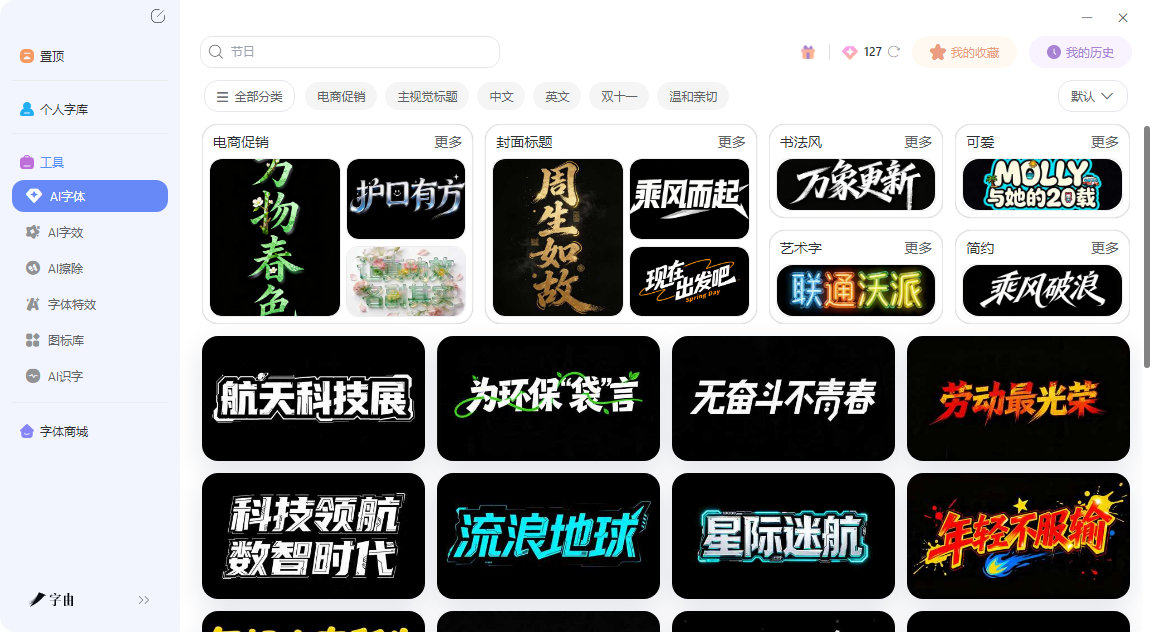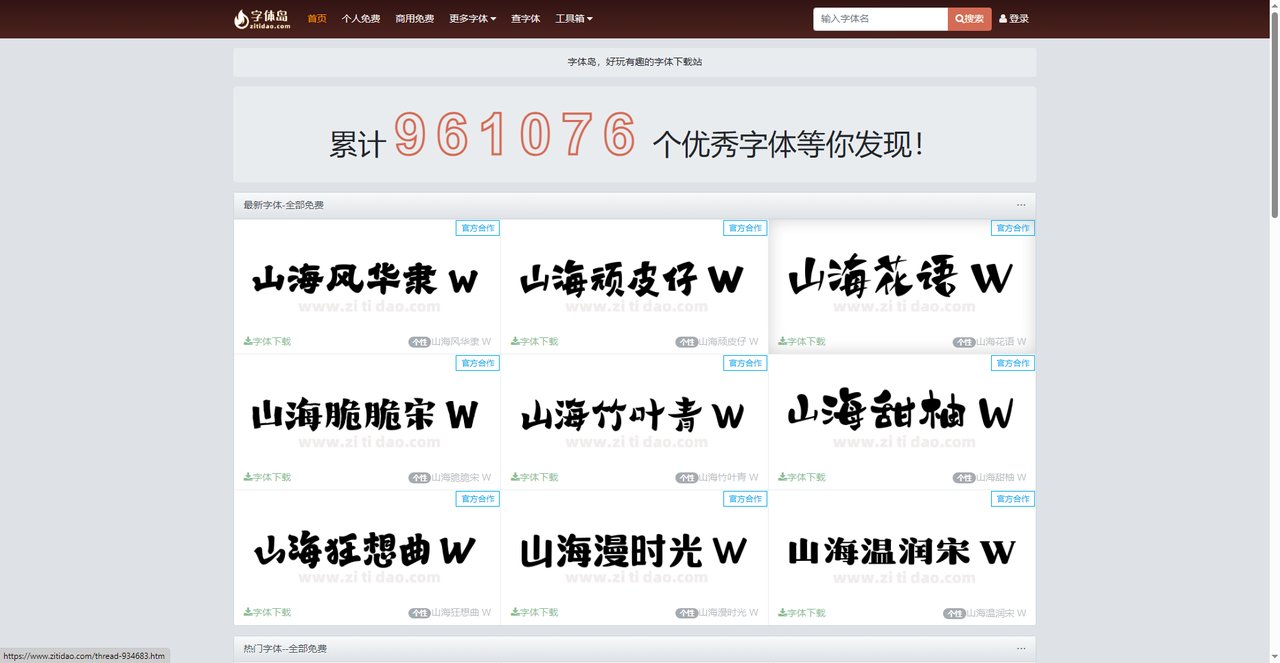
中文字体下载不用愁:看这篇中文字体下载网站精选
中文字体下载这件事,看起来简单,做起来全是坑。搜到一个字体站,点进去广告比内容多;好不容易找到下载按钮,下来一个压缩包,解压后还得自己判断放哪个文件夹;装完了打开PS发现字体没出现,又要重启软件。更麻烦的是,你永远不知道这款字体能不能商用——页面写着“免费”,但那个“免费”到底是免费下载还是免费商用?没人告诉你。这篇文章先介绍一个不用下载安装的方案——字由,然后补充4个传统下载站。看完你就知道,中文字体下载可以不用那么折腾。
打开字由客户端,上万款字体——包括中文字体——都在里面。字由收录了超过20000款字体资源,免费商用中文字体超过1000款,涵盖思源黑体、思源宋体、优设标题黑、阿里妈妈东方大楷等热门款。你只需要找到喜欢的字体,点一下“激活”,字体立刻出现在PS、AI、Word的字体列表里。不用解压,不用复制到C盘,不用重启软件。换电脑登录字由账号,之前激活的字体一键同步,不用重新下载。版权方面,字由专门做了“免费商用”筛选标签,点一下,所有能在商业项目里放心使用的中文字体一次性列出来。每款字体的详情页都有版权方的授权文件链接。
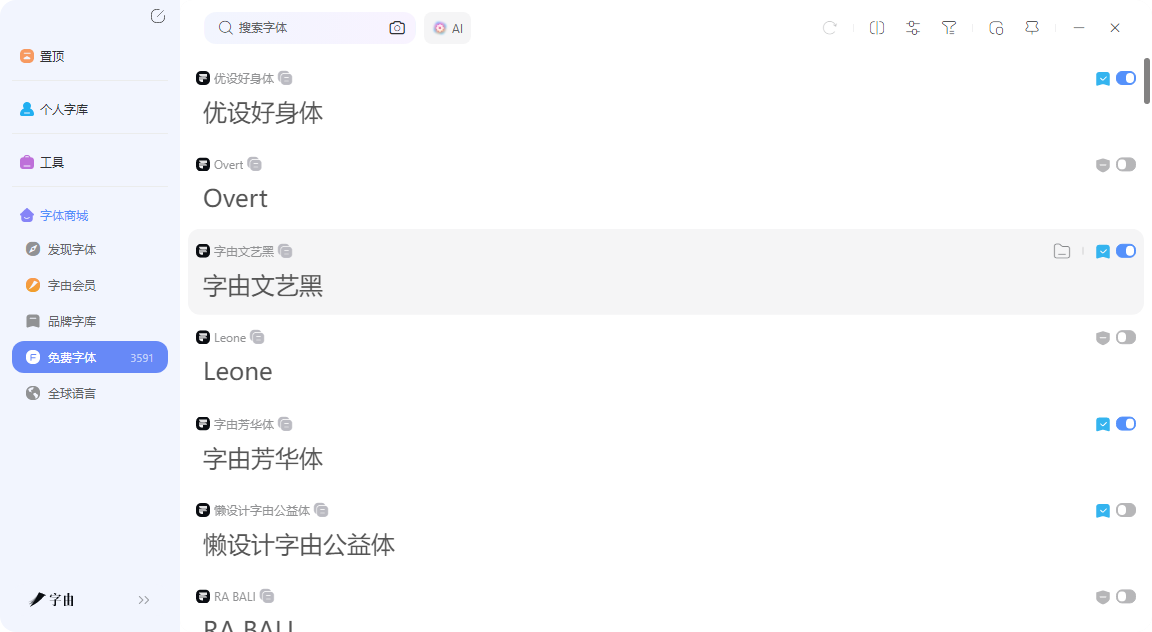
字由还有AI字体功能:输入文案,选个国潮风或书法模板,10秒生成一张艺术字图片,下载PNG就能用。这对那些不想折腾安装、只想快速出效果的用户来说,比传统下载站方便太多。
传统下载站不是不能用,但它们的模式停留在20年前。字由把“中文字体下载”这件事,从“搬运文件”变成了“云端激活”。你不需要关心字体文件存在哪、怎么传、怎么装。你只需要在字由里点一下“收藏”和“激活”,剩下的全部交给云端就可以了。
2、字体岛
第一个网站叫字体岛。打开首页,第一感觉是干净,没有那种满屏弹窗的廉价感。它主打“官方合作”字体,首页展示了山海风华隶W、山海顽皮仔W、山海花语W等一系列山海系列字体,风格偏个性、年轻化,适合做标题和海报。字体岛的特色在于它和字体厂商有直接合作,提供的字体不是网上随便扒来的,质量相对有保障。每款字体都标注了“免费”字样,下载前可以点击“个性”预览,看看实际效果。目前累计收录了96万+字体,数量可观,但实际去重后没那么多。下载方式还是传统的:点“字体下载”按钮,拿到压缩包,解压,安装。没有内置预览输入自己文案的功能,得下载后才能试效果。版权方面,首页写着“免费”,但没有明确区分“个人免费”还是“免费商用”,建议下载前自己核实一下。如果你需要一款有个性的标题字体,字体岛的山海系列值得翻一翻。
3、字海
第二个网站叫字海。它的定位更偏向设计师,分类维度很专业:按字体风格(未来、创意、经典、视觉、科技、灵感、传承)、按用途(阅读字体、标题字体、品牌字体、创意字体)、按语言(中文字体、日文字体、英文字体、韩文字体)等。字海最实用的功能是“字体预览/对比”。你可以同时选择多款字体,输入同一段文字,并排对比效果,不用一个一个点开看。这个功能在做字体选型的时候非常省时间。它还提供了“字体授权”科普板块,帮助用户了解字体版权知识,这一点比大多数下载站强。字海上的字体来源比较杂,有免费商用的,也有个人使用的,每款字体的详情页会标注授权类型,下载前需要仔细看。整体来说,字海适合那种“不知道用什么字体,需要慢慢翻、对比着选”的设计师。界面没有广告干扰,体验不错。
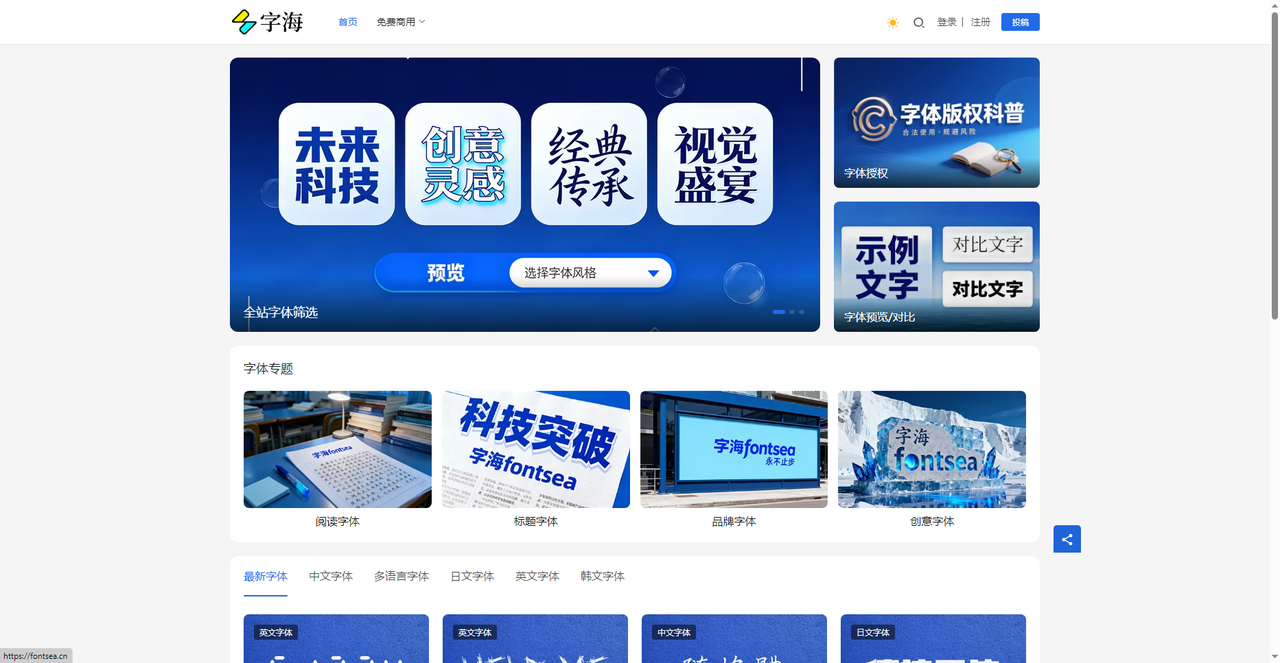
4、模板王
这个网站它目前收录了4033个中文字体,分类非常细:宋体、楷体、行书、隶书、黑体、草书、行楷、篆书、魏碑……按字体机构也分了方正、汉仪、微软、汉鼎、长城、华康、迷你等。每个分类下面都有大量字体,比如黑体490个、宋体425个。模板王的字体大多来自也字工厂、模板王自建字库等来源。展示的字体如“也字工厂专辑体”“也字工厂曲风体”“也字工厂意志体”等,风格偏现代、个性。下载方式传统,点击下载按钮拿压缩包。缺点是网站界面比较老旧,广告较多,而且字体的授权信息不够清晰,很多没有明确标注是否可商用。
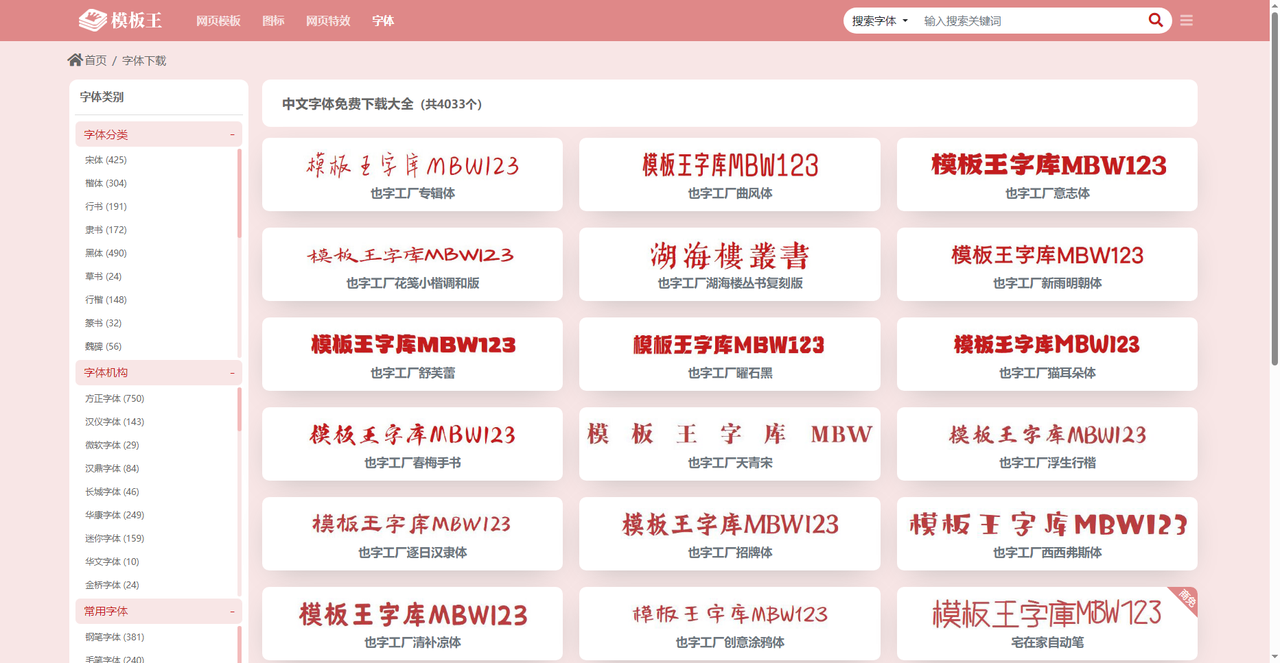
5、猫啃
第四个网站叫猫啃。这是一个专门做免费商用中文字体的网站,在设计师圈子里口碑不错。它自称已搜集8100款免费中文字体,首页展示“演示魁本楷”“演示系列免费商用字体”等,每个字体都标注了明确的授权类型,商用可以放心。猫啃还提供了“字体打包下载”功能,可以批量下载同类字体。整体来说,猫啃是目前国内最专业、最规范的免费商用中文字体站之一。如果你坚持传统下载安装的方式,猫啃是首选。但它依然逃不开传统流程。